»Eric-Gill-Serie« von Monotype
Mit der Eric-Gill-Serie präsentiert Monotype eine umfassende Schriften-Neuauflage. Die von Eric Gill geschaffene »Gill Sans« wurde unter anderem überarbeitet und erweitert.
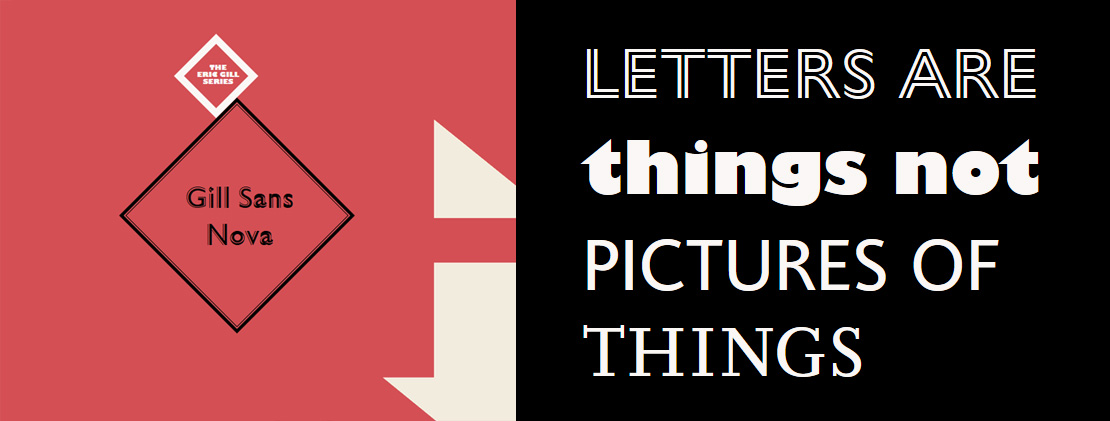
Die originale »Gill Sans« prägte die Kulturwelt visuell über Jahrzehnte und fand zuletzt Verwendung in populären Filmtiteln sowie in bekannten Marken.
Die vier Monotype Schriftdesigner Steve Matteson, George Ryan, Ben Jones und Terrance Weinzierl arbeiteten aus verschiedenen Teilen der Welt an der Eric Gill-Serie, um Gills Arbeiten für das 21. Jahrhundert neu zu beleben und sein Schaffen sowohl für digitale Kommunikationsmittel als auch für anspruchsvolle Print-Anwendungen fit zu machen. Das neue Paket besteht aus 77 Fonts und gliedert sich in die drei Familien Gill Sans Nova, Joanna Nova und Joanna Sans Nova.
Ähnlich wie bei Neuauflagen von Filmklassikern, bei denen Licht, Farbe, Sound und verlorene Szenen für heutiges Publikum digital wiederhergestellt werden, soll auch die Eric-Gill-Serie ein »Remastering« sein – ergänzt um neue Strichstärken und Glyphen für die internationale digitale Verwendung.
„Mit der Arbeit an der Schriften-Serie wertschätzt Monotype Vergangenheit, Gegenwart und Zukunft von Typografie und nutzt die einzigartige Möglichkeit, beliebte Klassiker mit neuen Schnitten, Zeichen und Sprachen für die Jetztzeit zu rüsten.“
Durch Original-Zeichnungen und -Material aus Gills Hinterlassenschaft, aufbewahrt in Monotypes historischem Archiv, sind viele Neuerungen von Gill selbst vorbereitet. Teil der Serie ist außerdem eine neue, von Gill inspirierte Schrift des Monotype Designers Terrance Weinzierl, die speziell für den Einsatz und die Lesbarkeit in digitalen Umgebungen entwickelt wurde. »Joanna Sans Nova« soll als Sans-Version die humanistische Tradition der »Joanna« fortsetzen.